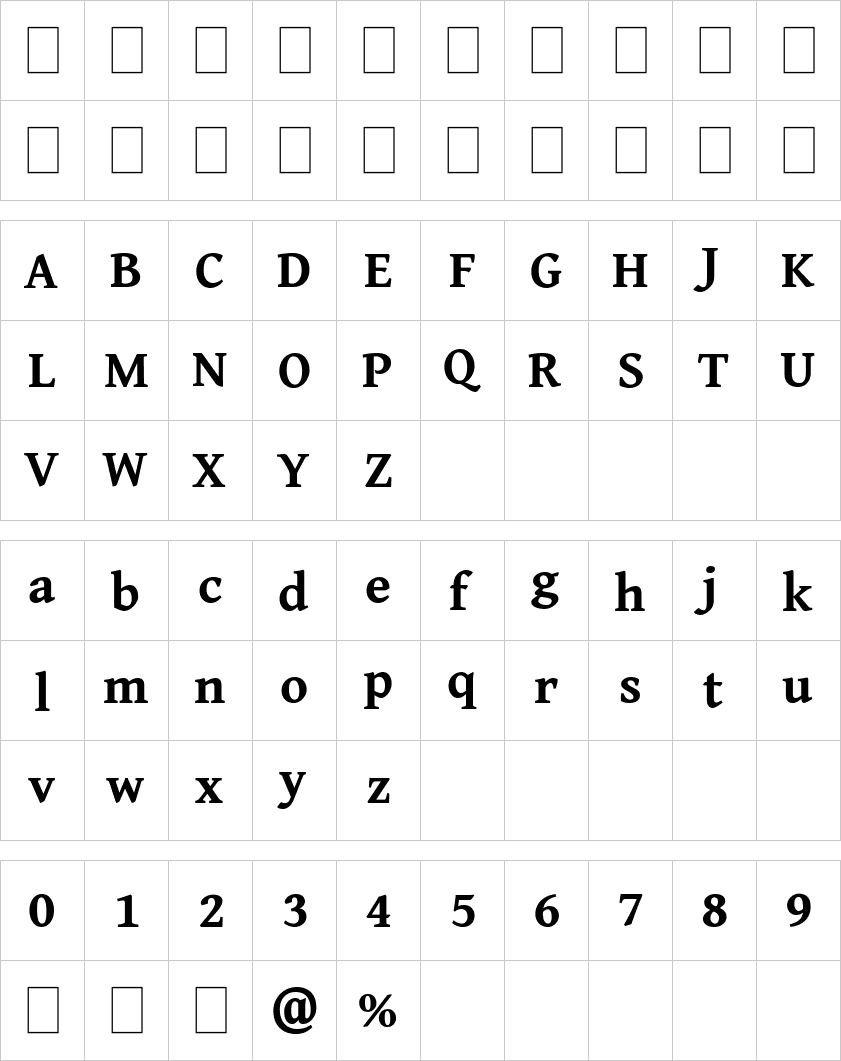
Gentium
Gentium是一种开源字体,由美国设计师Victor Gaultney创造,它的目的是为了提供一个易于阅读和具有国际性的字体,适用于各种语言和字符集。Gentium拥有广泛的Unicode支持,包括拉丁字母、基本和扩展的希腊字母、西里尔字母、亚美尼亚字母、格鲁吉亚字母和其他Unicode字符,这使得Gentium成为多语言文本的理想字体选择。
Gentium的设计简洁明快,字母形状和线条平滑,易于阅读。因此,它已成为许多学术出版物和在线文档中广泛使用的字体之一,也是许多开源软件和操作系统的默认字体之一。
Gentium Plus基于原始的Gentium设计,但扩展了字符和字形,并且几乎完全支持拉丁语,西里尔文和希腊语。
Gentium Plus经过精心设计,可支持三种字体的全系列字体,同时为其设计带来和谐。每种字体包含 4200 多个字形,并支持对多语言文本有用的高级 OpenType 功能,包括仔细的音调符号定位和小写字母。
拉丁文和西里尔字母用于书写世界各地的数千种语言。Gentium Plus为这些书写系统提供全面的支持,并包括对语言学和识字工作有用的各种附加字符和符号。Gentium Plus还支持希腊文字。